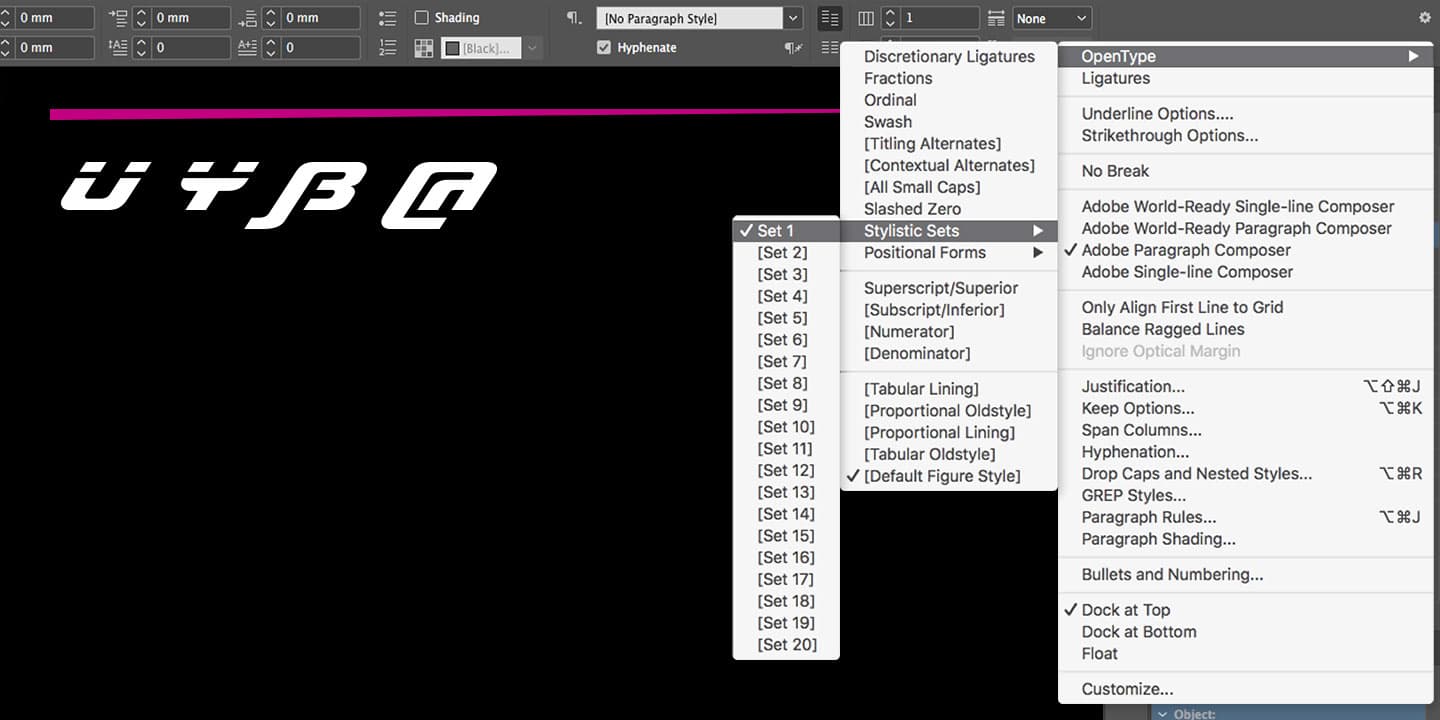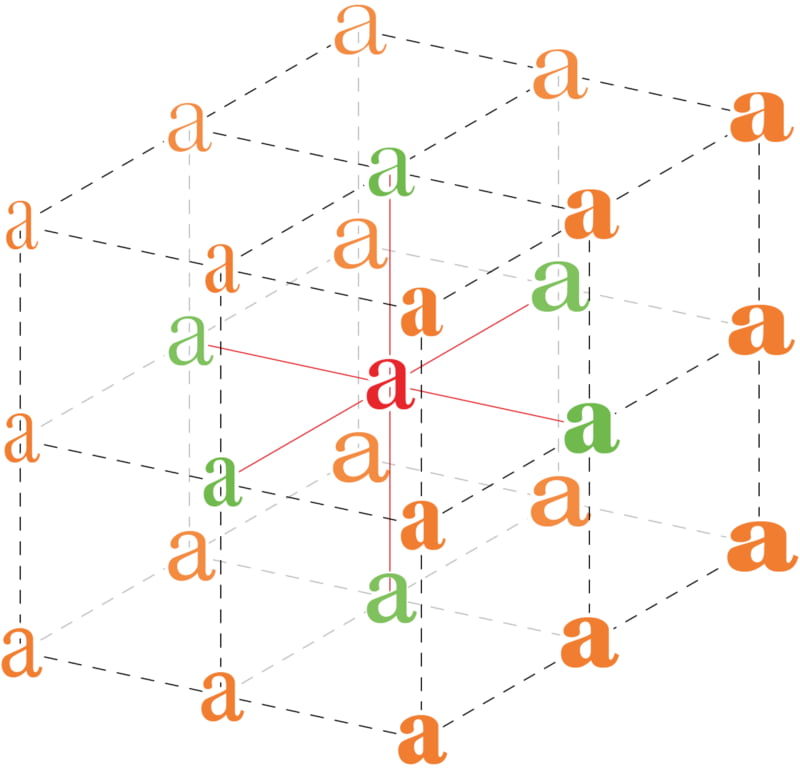
Typografie begrippenlijst
De complexe wereld van typografie
Welke vorm van typografie past bij jou?
Dit moet je weten voordat je een keuze maakt
Basis informatie
Wij ontwerpen custom fonts voor Nederlandstalige klanten. Daarom geven wij in deze typografie begrippenlijst zo uitgebreid mogelijk uitleg over typografie, custom fonts en jouw voordelen als klant.
Anatomie van een lettertype
Deze begrippen beschrijven de verschillende onderdelen van een lettertype. De termen, en de delen van de letter die ze beschrijven, worden de ‘anatomie van een lettertype’ genoemd. Door de letters in anatomie elementen op te breken, kan iedereen beter begrijpen hoe een letter gecreëerd wordt en hoe je deze kennis zo effectief mogelijk inzet.
Taalondersteuning
Merken worden steeds meer internationaal. Jouw custom font moet daarom alle talen spreken van de landen waarin jouw bedrijf actief is.
Wij ontwikkelen brandfonts met de onderstaande taalondersteuning. De character sets (beschikbare lettertekens) kunnen met elkaar gecombineerd worden voor een groter taalgebruik. Wij adviseren je graag hierin.
Language Support
In principe kunnen wij alle talen aan jullie custom font toevoegen die gewenst zijn. Alle Latin talen maken wij zelf. Voor alle overige talen zoals Russisch, Chinees, Thais, etc halen wij een font specialist bij het project. Deze talen zijn zeer specialistisch en moeten door natives gecontroleerd worden.
De onderstaande Latin character sets bieden wij standaard aan. Deze kunnen gecombineerd worden voor een groter taalbereik.
Wij kunnen ook helemaal zelf jullie character set samenstellen, maar voor het gemak hebben wij deze opgedeeld in grote blokken van het Europese taalbereik.
Basic Latin (West-Europees) character set
Deze set bevat 97 lettertekens en kan voor meer taalbereik uitgebreid worden met de Latin – 1 Supplement en Latin Extended – A character sets:
!”#$%&'()*+,-./0123456789:;<=>?@
ABCDEFGHIJKLMNOPQRSTUVWXYZ[\]^_`
abcdefghijklmnopqrstuvwxyz{|}~¤€£
13 ondersteunde talen
Deens, Duits, Engels, Frans, IJslands, Italiaans, Nederlands, Noors, Maleis, Portugees, Spaans, Swahili, Zweeds.
Latin - 1 Supplement character set
Deze set bevat 90 lettertekens en is een uitbreiding op de Basic Latin character set:
ÀÁÂÃÄÅÆÇÈÉÊËÌÍÎÏÑÒÓÔÕÖØÙÚÛÜÝÐÞàáâãäåæ
çèéêëìíîïñòóôõöøßùúûüýðþµ¡¿
«»-·¦§¶©®¹²³ªº°¼½¾×÷±¬´¨¯¸
21 ondersteunde talen
Afrikaans, Baskisch, Bretons, Catalaans, Deens, Duits, English, Fins, Frans, Gaelic, Iers, Italiaans, IJslands, Maleis, Nederlands, Noors, Portugees, Spaans, Saami, Swahili, Zweeds.
Latin Extended - A character set
Deze set bevat 127 lettertekens en is een uitbreiding op de Basic Latin character set:
ĀĂĄĆĈČĊĎĐĚĒĔĖĘĜĞĠĢĤĦĨĪİĮĬĴĶĹĽĻĿŁŃŇŅŌŐŎŒŔŘŖŚŜŠŞŤŢŦ
ŨŪŬŮŰŲŴŶŸŹŽŻŊIJ
āăąćĉčċďđěēĕėęĝğġģĥħĩīįĭıĵķĸĺľŀļłńňņʼnōőŏœŕŗřśŝšşťţŧũūŭůűųŵŷźžżŋij
43 ondersteunde talen
Afrikaans, Baskisch, Bretons, Catalaans, Deens, Duits, Engels, Esperanto, Estisch, Finnen, Frans, Gaelic, Groenlands, Hongaars, Iers, Italiaans, IJslands, Kasjoebisch, Koerdisch, Kroatisch, Lets, Litouws, Maleis, Maltees, Nederlands, Noord-Samic, Noors, Pools, Portugees, Roatiaanse, Roemeens, Servisch, Spaans, Saami, Sloveens, Slowaaks, Sorbisch, Swahili, Tsjechisch, Turks, Tsjechisch, Welsh, Zweeds.